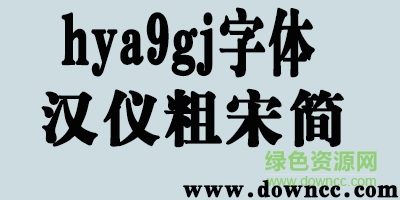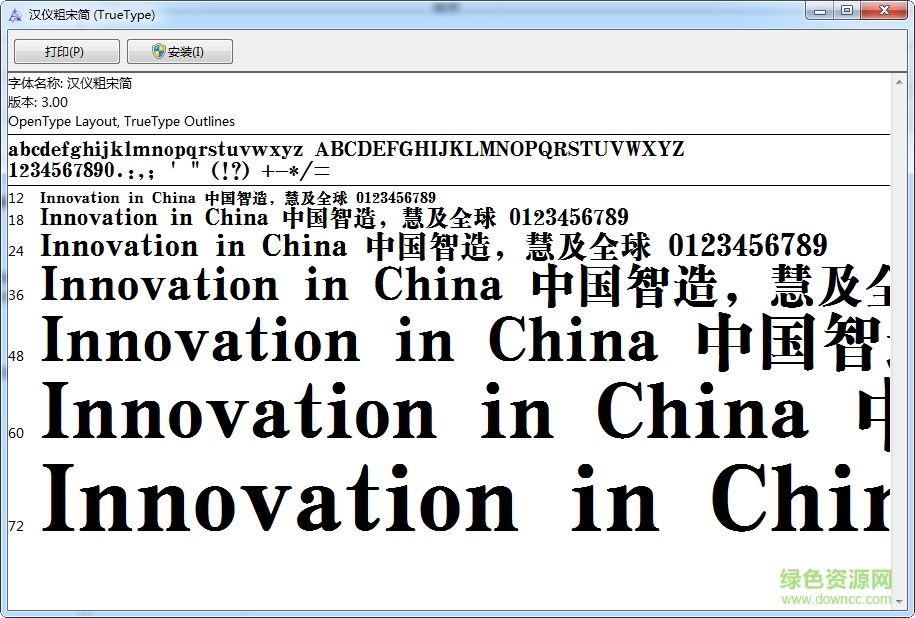
hya9gj字體也就是漢儀粗宋簡(jiǎn)體字體,這款字體端正大方,筆畫粗壯,跟宋體相似,但又有其自己的特色,喜歡這款字體的朋友可以來綠色資源網(wǎng)免費(fèi)下載體驗(yàn)喲!
hya9gj字體一款非常經(jīng)典的簡(jiǎn)體字體,大氣時(shí)尚,寫出來的字體醒目流暢,看起來美觀,并且適用的范圍非常廣泛,喜歡的朋友就來綠色資源網(wǎng)下載吧。